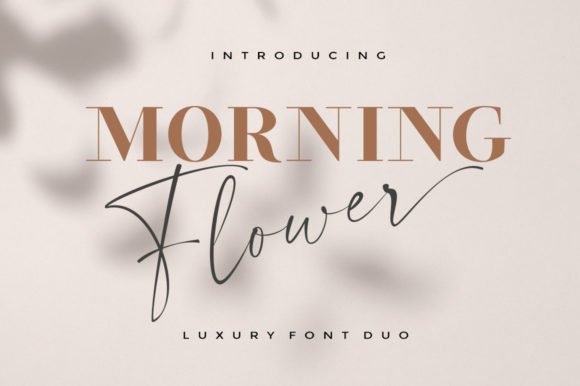
[Creativefabrica] Morning Flower Font (2021)
Morning Flower Duo - роскошный дуэтный шрифт (шрифт и засечка).
В нем великолепно сочетаются изысканность и напористость.